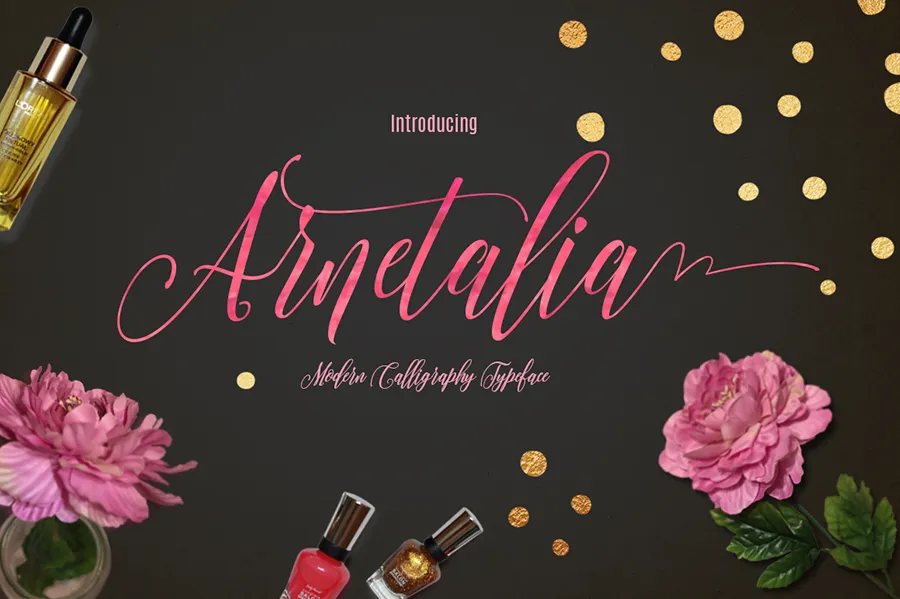
Arnetalia Font – Download Grátis
A Arnetalia é uma elegante tipografia de escrita aquarelada moderna com estilos de escrever naturalmente e caracteres que balançam inconstituentemente. Esta script é perfeitamente adequado para adicionar um toque pessoal em qualquer projeto atual, como convites de casamento, cartas de cumprimento, diários de scrapbooking. A Arnetalia é uma escolha ideal para aqueles buscando um estilo criativo e autêntico sem comprometer a legibilidade da sua tipografia. É perfeita para quem aprecia uma mistura suave de modernidade e artesanato, fazendo-a um verdadeiro complemento em qualquer projeto gráfico.